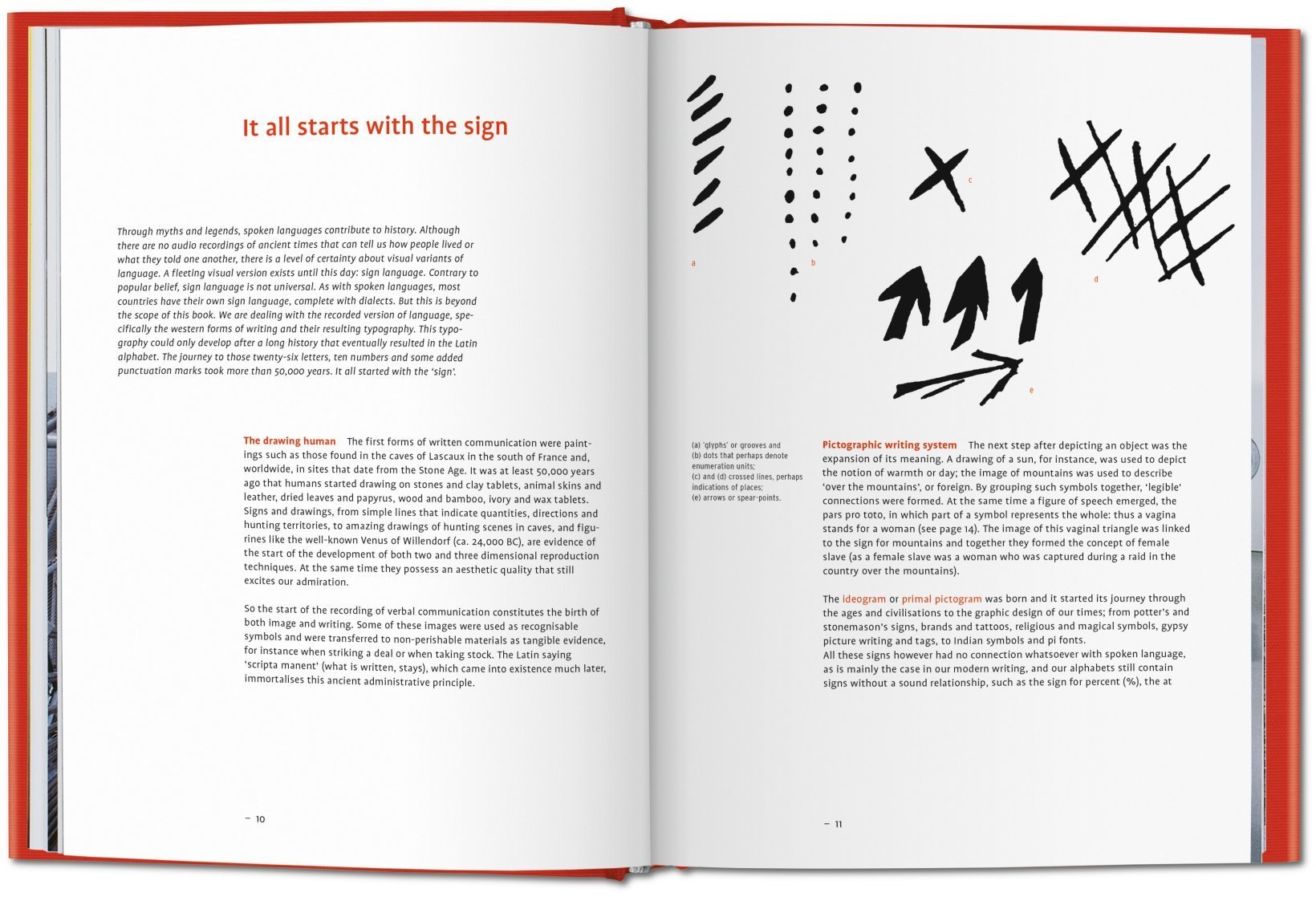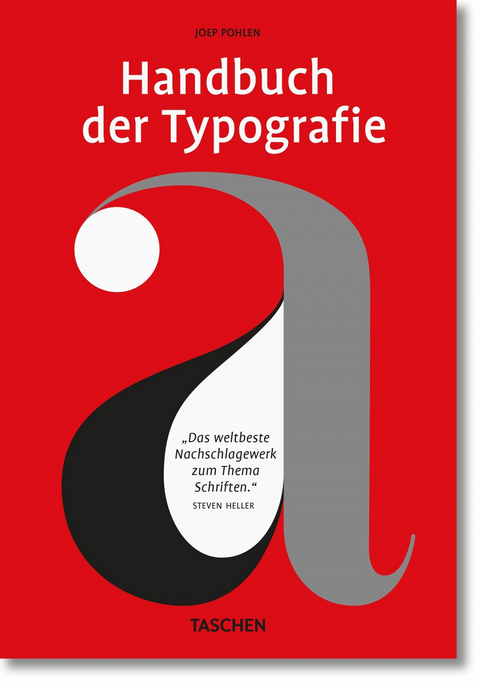
Eine Neuauflage unseres preisgekrönten Schriftenhandbuchs. Neben der Untersuchung von über 150 Schriften anhand von Form und Anatomie jedes Buchstabens einschließlich Satz- und Sonderzeichen, verortet dieser Must have-Guide Typografie in einem breiteren kulturellen Kontext. Ergänzt wird das Ganze durch einen Index von 250 Schriftdesignern, eine...